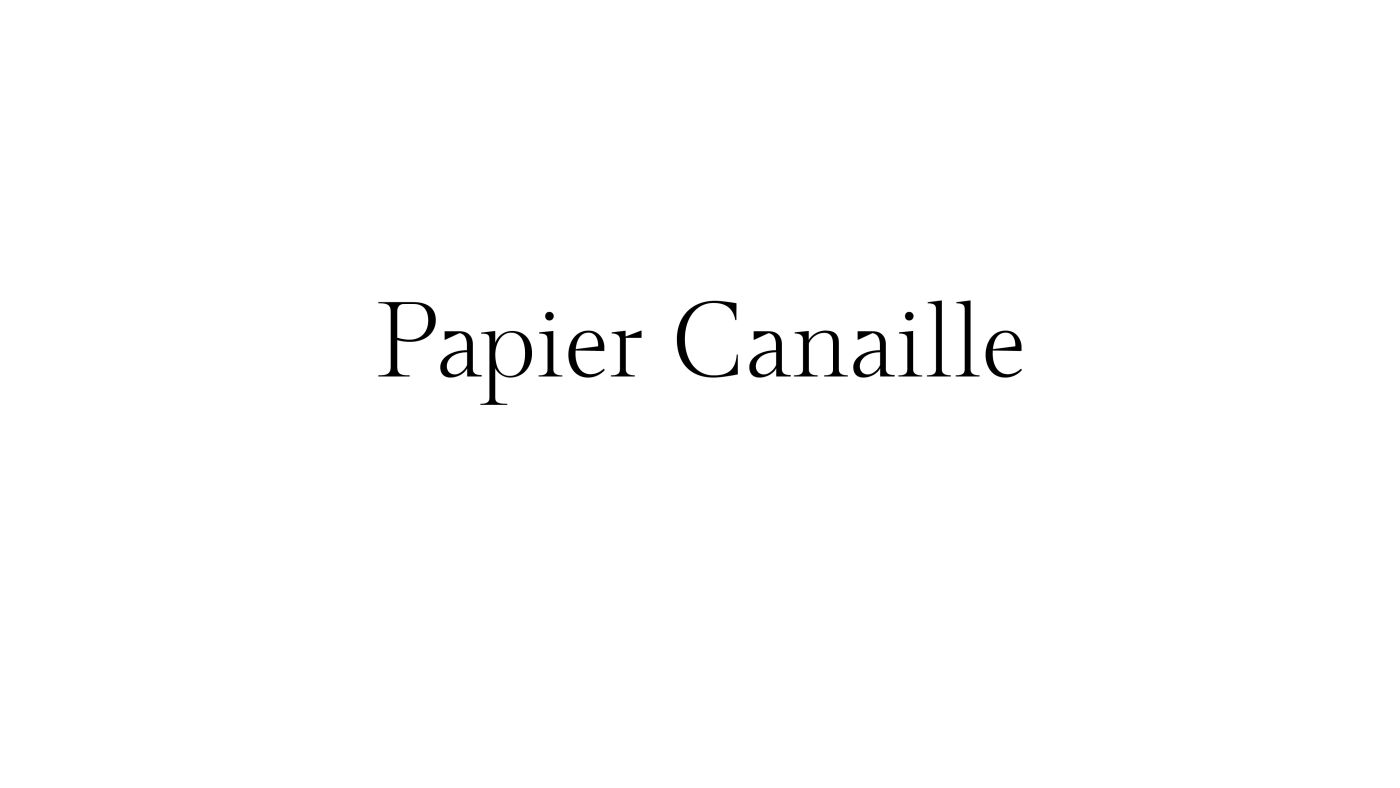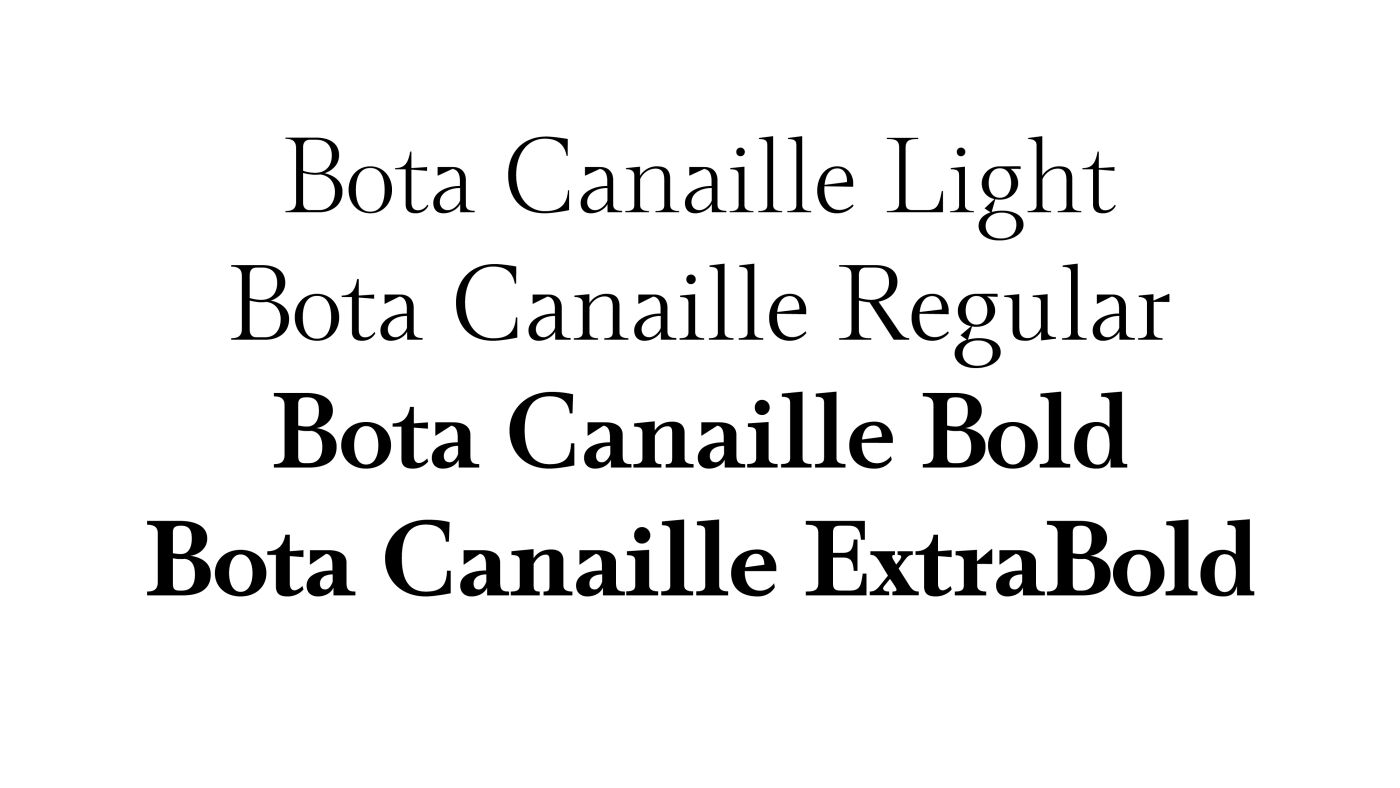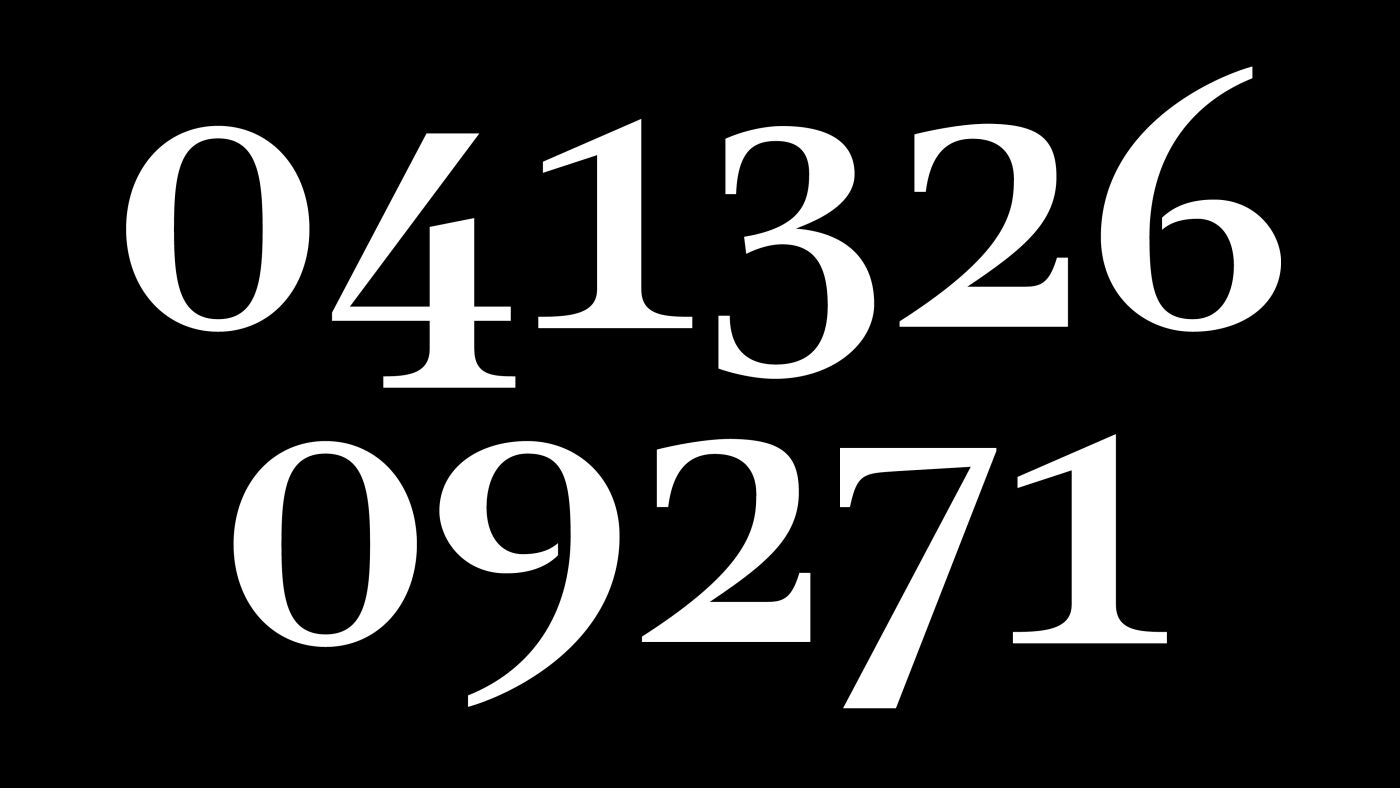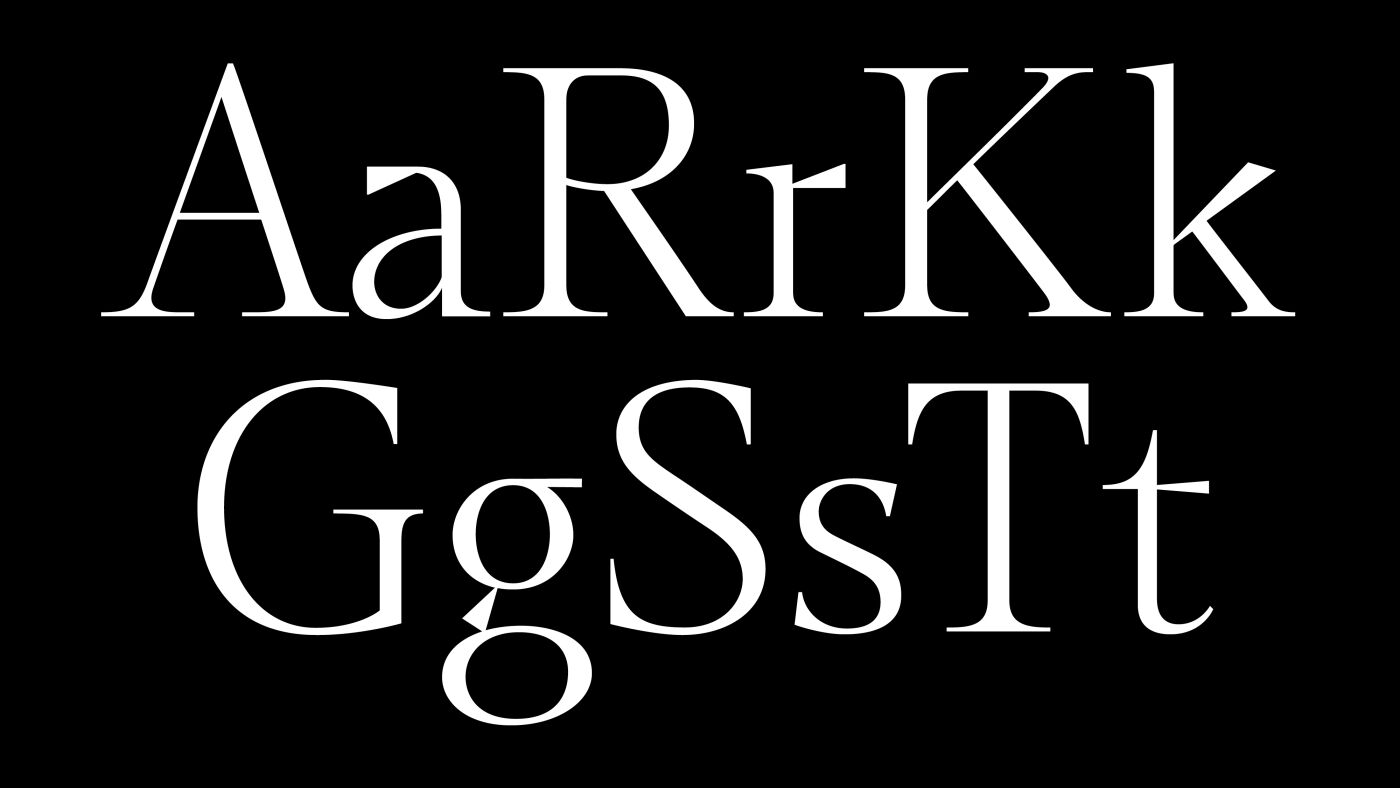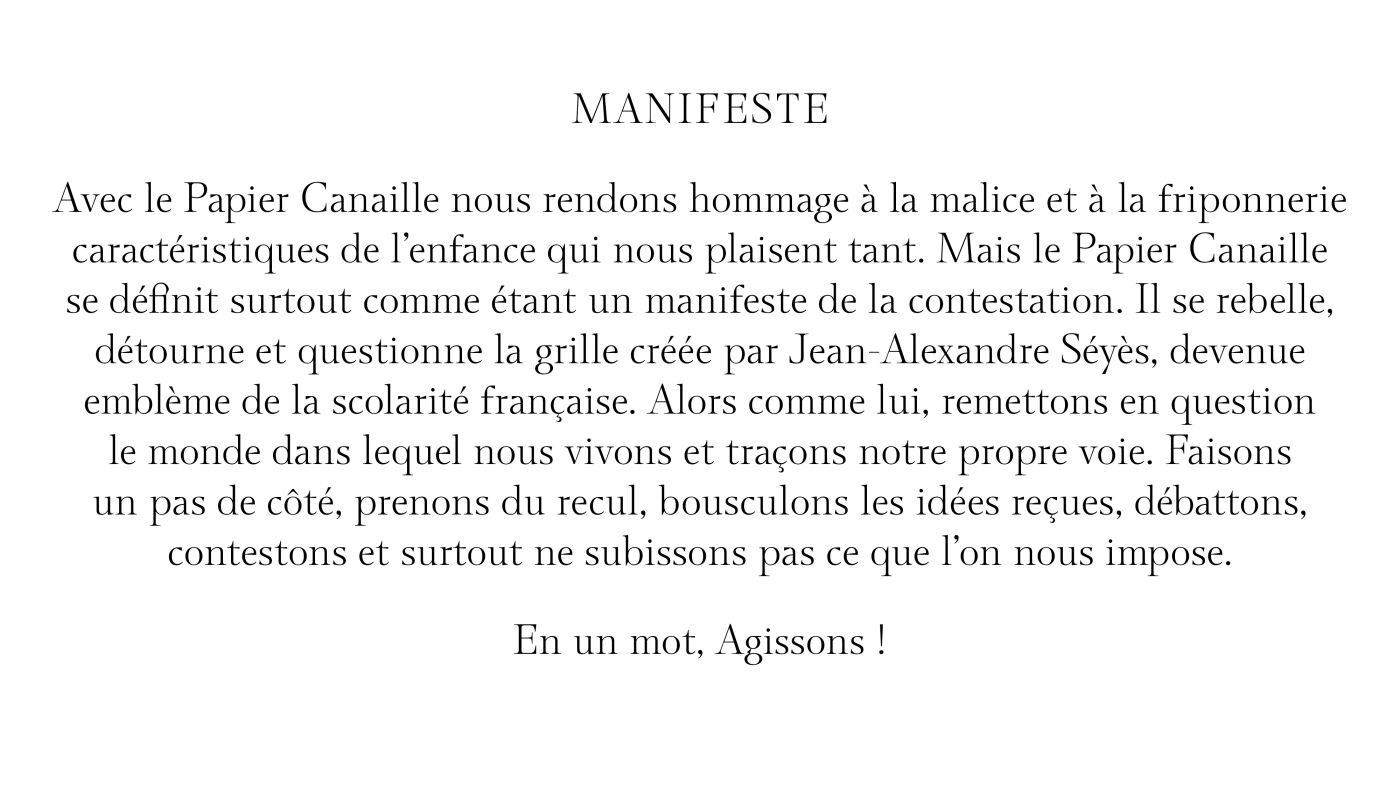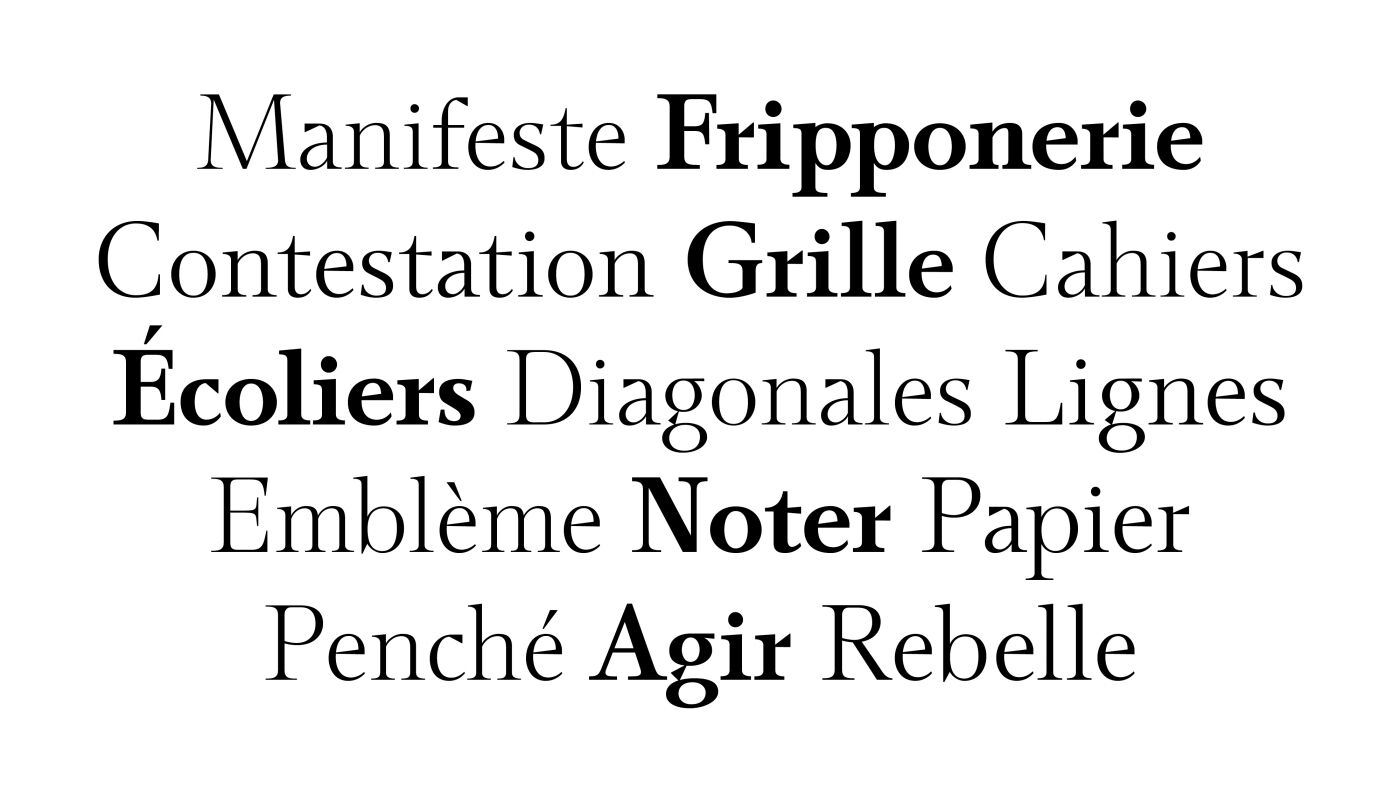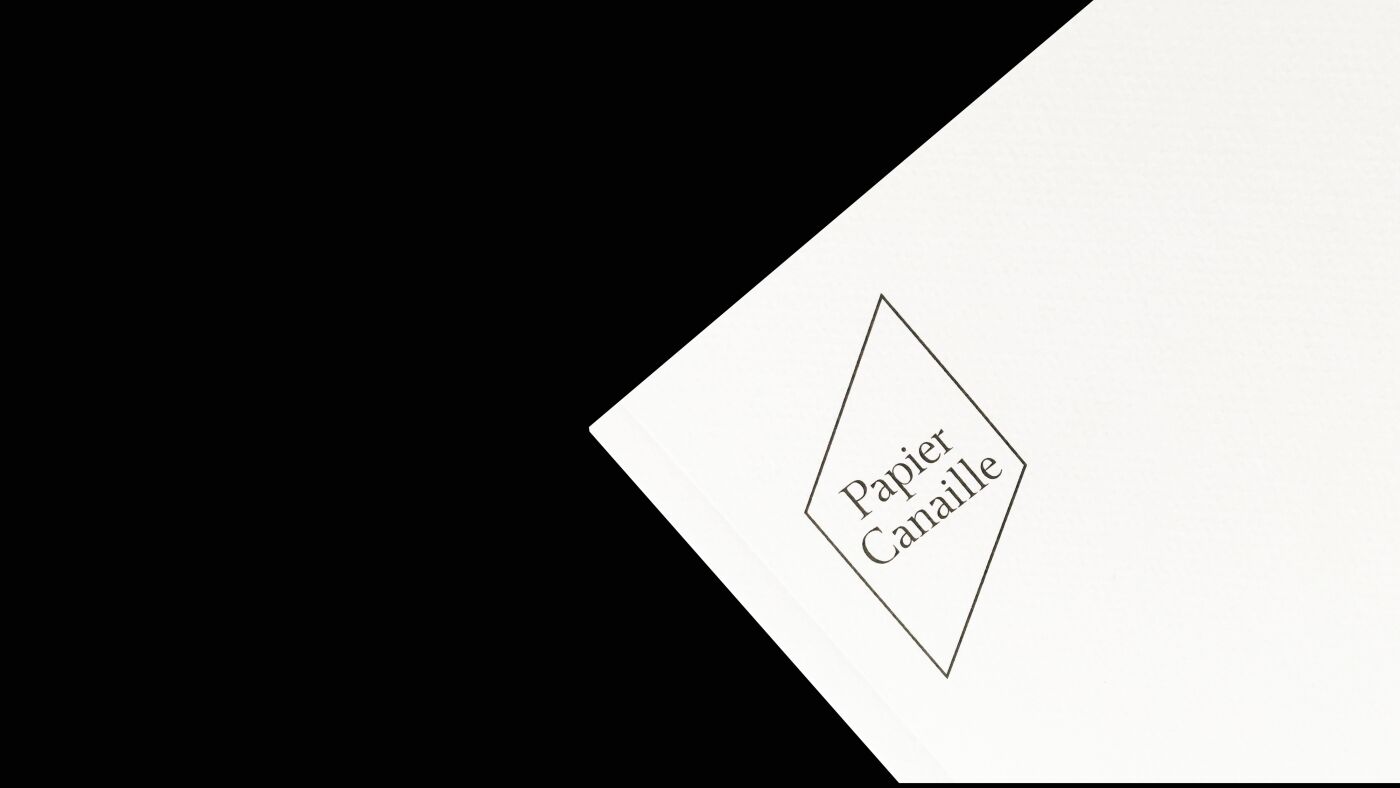
Bota Canaille, typographie sur-mesure
Papier Canaille est une marque de papeterie française qui édite
des cahiers inspirés de ceux des écolièrs.
En revanche les lignes ne sont plus droites !
La marque se dote de la Bota Canaille une typographie sur-mesure